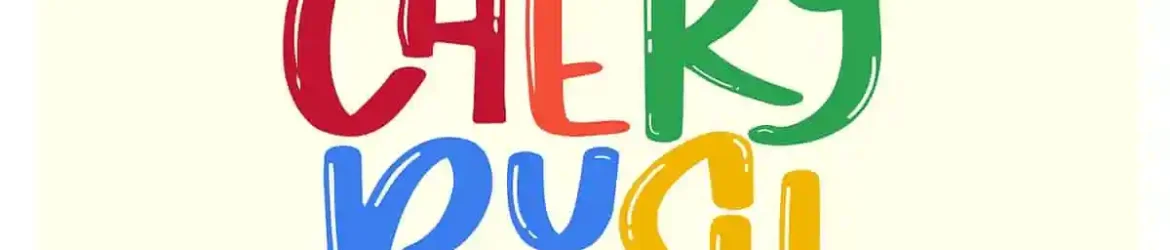
Chery Rush Display Font – Download Grátis
A Chery Rush é uma fonte criada pelo D&K_project, projetada para ser divertida e alegre. Conhecida por sua mistura de maiúsculas e minúsculas, esta fonte oferece muitas possibilidades de combinações, tornando-a perfeita para uso em grandes exibições. Seus traços suaves e sua disposição leve fazem dela uma opção ideal não apenas para logotipos e rótulos divertidos, mas também para sinalizações infantis ou qualquer projeto que envolva letras. A Chery Rush é perfeita para aquelas produções que procuram um toque de diversão e criatividade em seus materiais gráficos.